Phong chữ miễn phí Việt hóa đẹp tháng 3/2025
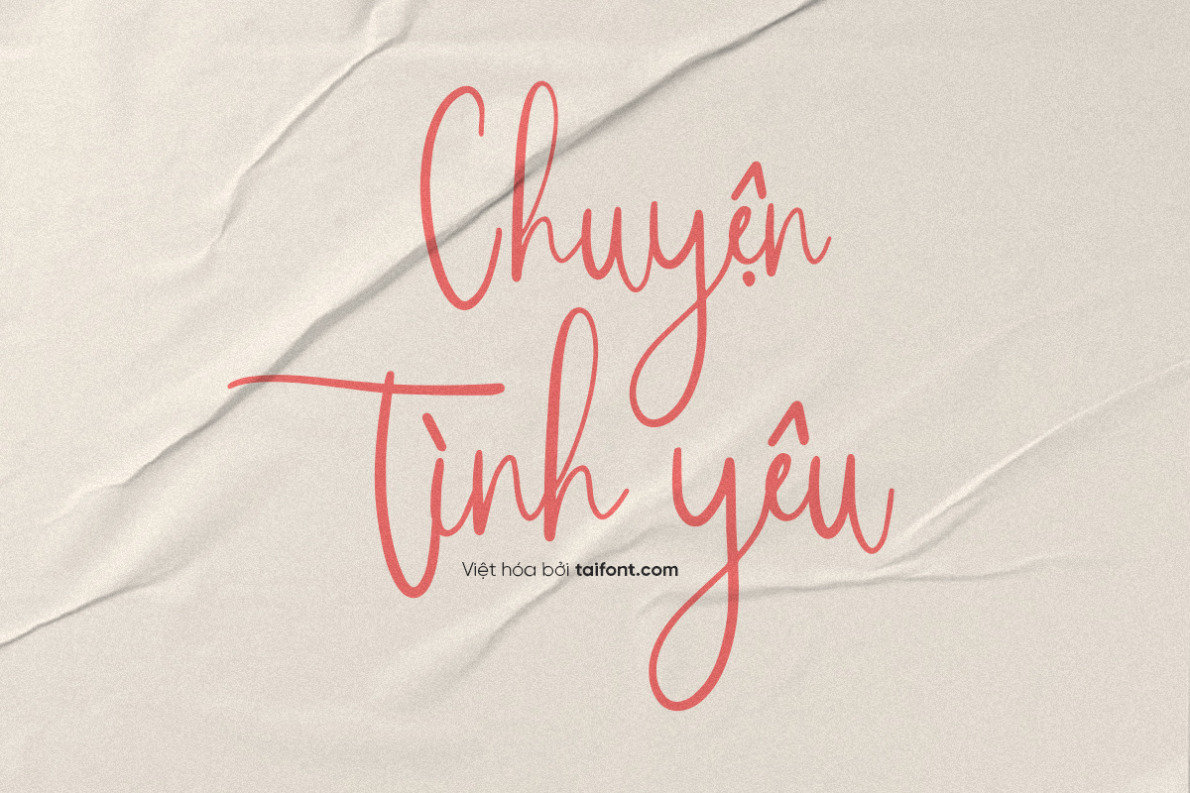
Phong Chữ Miễn Phí Việt Hóa Đẹp Tháng 3/2025: Bộ Sưu Tập Dành Cho Các Designer
Nếu bạn đang tìm kiếm những phong chữ miễn phí, đẹp và đặc biệt là đã được việt hóa để phục vụ công việc thiết kế của mình, thì bài viết này là dành cho bạn. Dưới đây là bộ sưu tập phong chữ miễn phí Việt hóa đẹp tháng 3/2025 mà các designer không thể bỏ qua.
1. Font UTM Bebas – Font Không Chân Dành Cho Thiết Kế
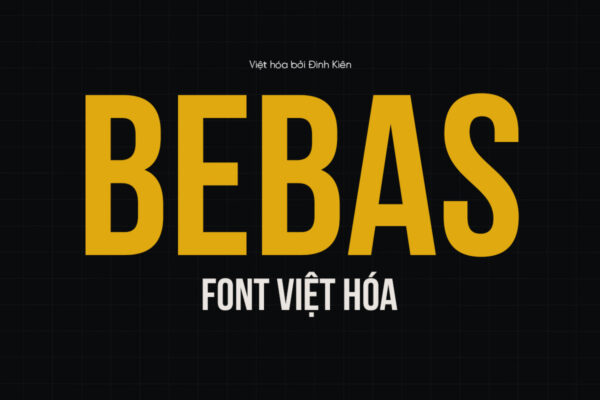
Font UTM Bebas là một trong những phong chữ không chân phổ biến, được sử dụng rộng rãi trong các thiết kế hiện đại. Với kiểu chữ mạnh mẽ, rõ ràng, UTM Bebas đặc biệt phù hợp với những dự án thiết kế cần sự mạnh mẽ, rõ nét như poster, banner, quảng cáo, logo, hay tên thương hiệu.
Điểm nổi bật của font này là sự đơn giản nhưng đầy ấn tượng, giúp truyền tải thông điệp một cách mạnh mẽ và dễ nhận diện.
- Ứng dụng: Thiết kế quảng cáo, poster, banner, logo.
2. Font TF South Rose – Font Viết Tay Cho Thiết Kế Thiệp Cưới
TF South Rose là font viết tay với phong cách nhẹ nhàng, tinh tế, rất thích hợp cho những dự án thiệp cưới, thư mời, hay các ấn phẩm liên quan đến sự kiện trọng đại. Với các đường nét mềm mại, uyển chuyển, TF South Rose sẽ mang đến một vẻ đẹp sang trọng, lãng mạn cho các thiết kế của bạn.
- Ứng dụng: Thiết kế thiệp cưới, thiệp mời, giấy mời sự kiện.
3. Font Laga Signatica – Font Viết Tay Cho Thiết Kế Thiệp Mời
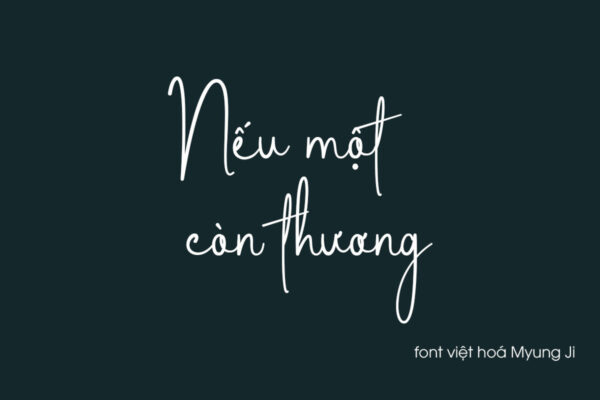
Font Laga Signatica là một lựa chọn tuyệt vời nếu bạn cần một phong chữ viết tay mang tính cá nhân hóa cao cho các thiết kế như thiệp mời hay thiệp sinh nhật. Với những đường cong tinh tế, font này tạo ra sự mềm mại và nhẹ nhàng, rất phù hợp cho các sản phẩm in ấn mang tính chất trang trọng và nghệ thuật.
- Ứng dụng: Thiết kế thiệp mời, thiệp sinh nhật, ấn phẩm sự kiện.
Tại Sao Nên Sử Dụng Phong Chữ Miễn Phí Việt Hóa?
Kết Luận
Bộ sưu tập phong chữ miễn phí việt hóa đẹp tháng 3/2025 này chắc chắn sẽ là lựa chọn lý tưởng cho các designer đang tìm kiếm những font chữ độc đáo, dễ sử dụng và phù hợp với các dự án thiết kế đa dạng. Hãy tải về và trải nghiệm ngay các phong chữ như UTM Bebas, TF South Rose, và Laga Signatica để làm mới những tác phẩm thiết kế của bạn.